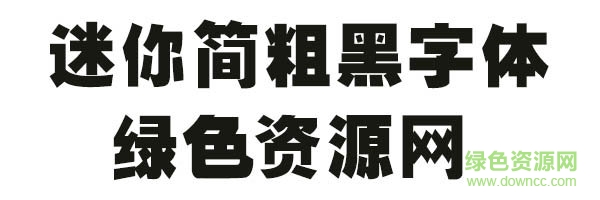
迷你簡粗黑字體是一款粗體藝術(shù)字體,適合用來作為文章的重點(diǎn)段落、句子使用,廣告設(shè)計(jì)也可以作為標(biāo)題使用,有需要的朋友們不要錯過喲,快來綠色資源網(wǎng)踴躍下載吧!
迷你簡粗黑字體是由黑體演變而來的,所以說他也有黑體的雄厚壯實(shí),線條非常的粗厚,給人一種獨(dú)有的安全感。